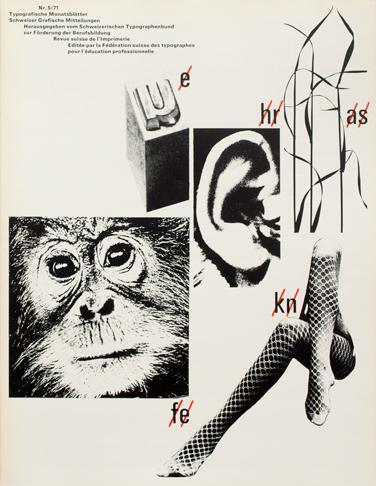
Microboy, das hast du alles mit Grid Type entworfen?
Nein, nein … ich hab ChatGBT zu Grid Type gebrieft und die brauchbaren Ergebnisse dann im Copyshop drucken und binden lassen.
Ausgehend von dem heutigen Artikel zum Atlas of Typography habe ich das äußerst interessante Interview zur griechischen Typographie gelesen und bin meiner Neugierde nachgegangen. Dabei habe ich dieses Digitalisat einer Probe der Tauchnitz-Druckerei entdeckt. Diese Druckerfamilie hat dem Interviewten nach auf Jahrzehnte hinweg griechische Typographie in Deutschland geprägt mit ihrer sehr geneigten Schrift, die ich bis dato immer hilfsweise als "Teubner-Griechisch" bezeichnet hatte, da sie mir typisch für die Drucke des Teubner-Verlags waren:
Bruno Güttinger, Titelentwurf, Typografische Monatsblätter, Nr. 5/71
(Würde auch zu »Kniffliges Wort« passen.)
Typ(e)
O(hr)
Gr(as)
Af(fe)
(K)aro-Strumpfhose(n) :hammer:
Bravo, 1 mit Stern. ; )
Capitals Monumentalis … schön wär’s! Sieht eher aus wie die Times. Es sieht zumindest so aus, als hätte das C unten keine Serife. Wer bei LinkedIn ist, kann auch unter dem Post von Nora Gummert-Hauser (Prof. für Typografie an die Hochschule Niederrhein) seine Kommentare loswerden ;-)
Das Thema ist sogar bis zu Fastcompany durchgedrungen. Typo ist wieder Mainstream.
Wie die üble Zurichtung passieren konnte, wird in dem Artikel visuell demonstriert:
Der Abstand zwischen den äußersten Vektorpunkten zweier benachbarter Buchstaben wurde demnach einfach immer identisch gesetzt – “the most boneheaded rookie mistake you can imagine (pun intended)”.
Mit einer richtigen AllCaps™ wäre das nicht passiert. Dazu als stilistische Alternative von U auf V umschalten und das Problem wäre nicht aufgetaucht. Ich sehe im Laufe der Zeit eine zunehmende Zahl von Argumenten für solide AllCaps und SmallCaps in Schriftfamilien. Diese könnten mehr Mehrwert bringen als (fettschräge) Bold-Italic?
Wenn derjenige, der die Times New Roman als Vorlage für den Stein verwendet hat, nicht sämtliche Buchstabenabstände vereinheitlicht hätte, wäre das auch nicht passiert.
Ja, aber ich hätte für eine solche Grabstätte einen erfahrenen Meistersteinmetz erwartet. Diese Fachleute wissen, wie man Versalien spationiert. An einem Ort wie dem Vatikan gibt es doch ständig Inschriften zu fertigen, würde ich denken … Erstaunlich! :-?